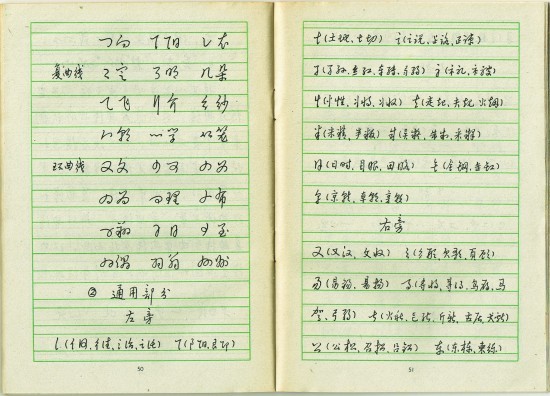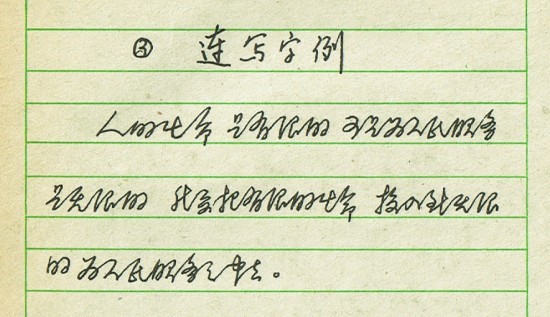
中文の古本を眺める(4)『漢字快写法』
4冊目は黄若舟編著・書『漢字快写法』。1983年8月発行、定価0.22元で、上海書画出版社出版。
書名にあるように、この本のテーマは「漢字を速く書く方法」。万年筆(钢笔 )やボールペン(圆珠笔 )など硬筆での筆記を想定しており、常日頃のメモなどに役立つような実用的な内容。
「速く書く方法」といっても別に裏技があるわけではなく、行楷・行草・草書の順に基礎から学んでいく。下の画像のように、本文も左横書き簡体のペン字で書かれている。
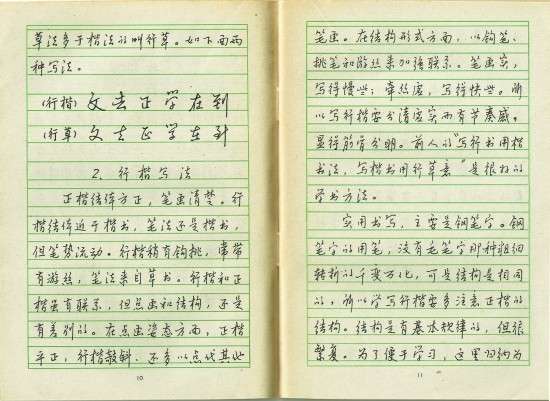
内容は、日本で売っている「行書入門」「草書入門」といった類の本と同じような感じ。
一番最後には「詞語連写」という節があり、語句ごとに繋げて書く方法が解説されている。横書きの連綿とは珍しい。この画像が詞語連写の例だが、見てのとおり何とも変態的。
果たしてどれだけ読めるだろうか。答えは以下に隠しておく。
人的生命 是有限的 可是为人民服务 是无限的 我要把有限的生命 投入到无限的 为人民服务之中去。
このような連綿がどの程度一般的なのかという点については、現状をよく知らないので何とも言えない。ただ、(芸術としての書以外では)ほとんどが横書きになった現代の中国で、新しい書体・書法が生まれてきても不思議ではないと思う。